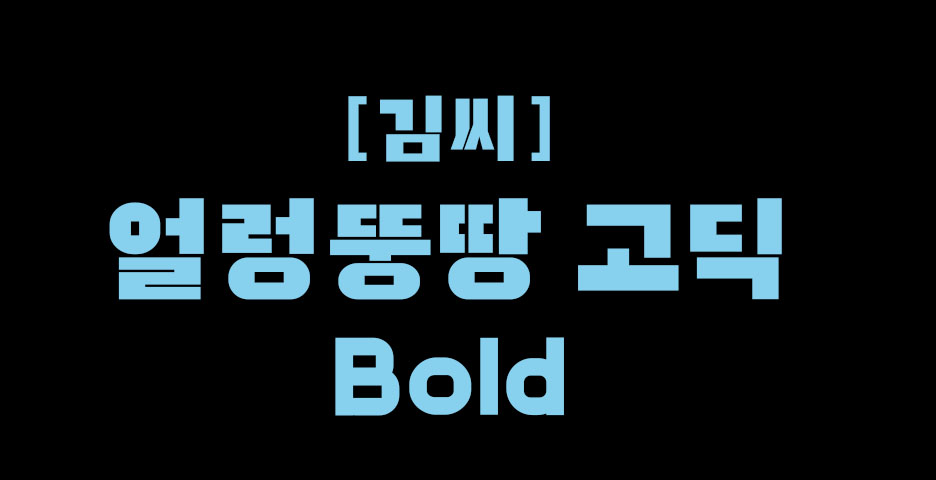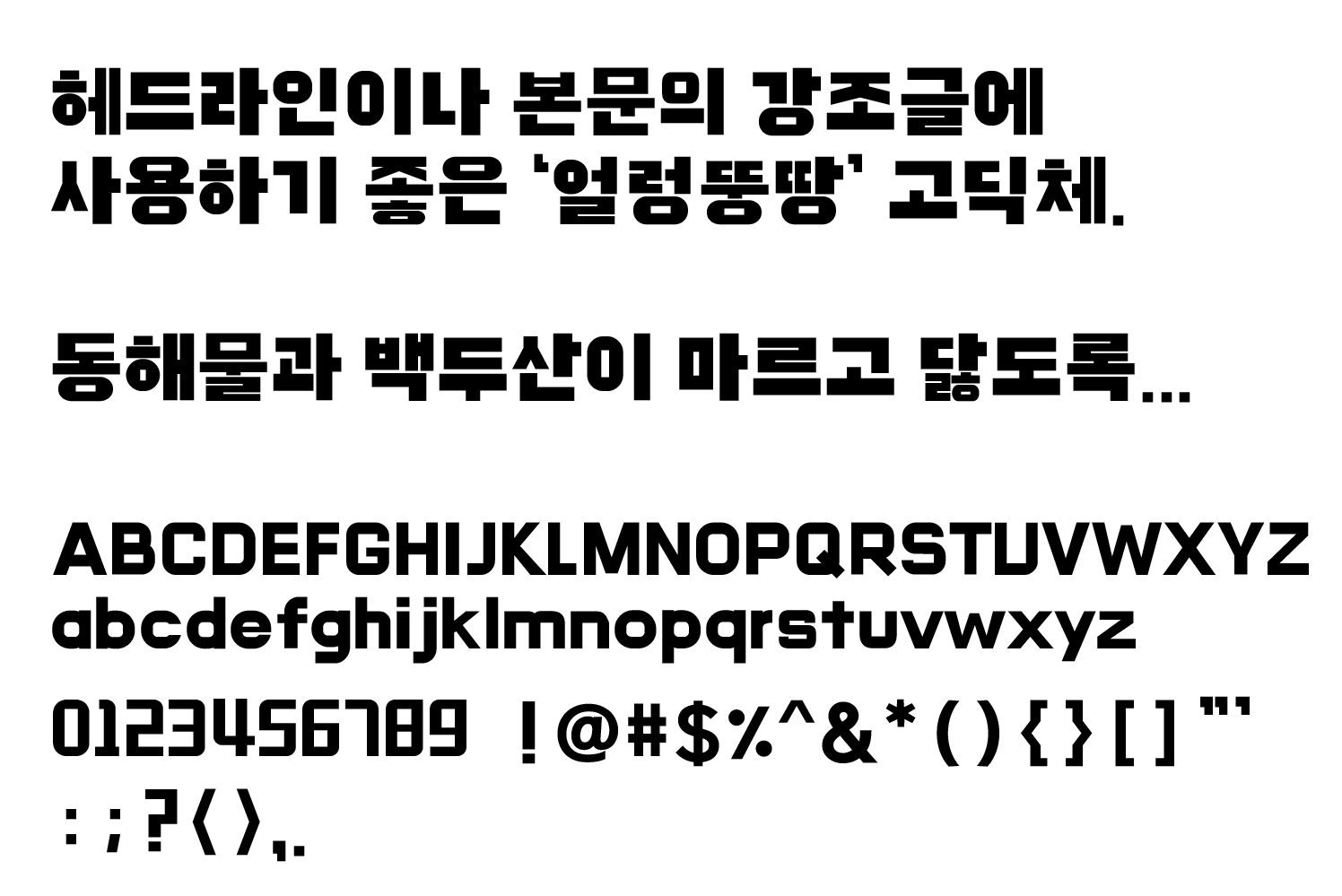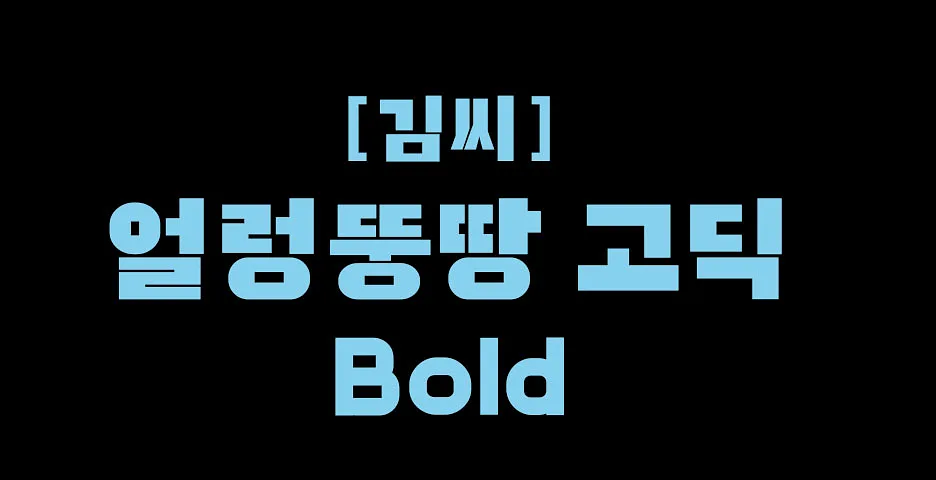
●● 폰트 특성
- 강함 / 명확함 / 신뢰감을 컨셉으로 글꼴 설계
- 전체적으로 곡선을 최소화하고 직선적인 굵은 획을 사용해서 시각적인 무게감이 느껴지도록 디자인.
- 글꼴의 장평비례가 조금 넓게 디자인되어서 문장이 답답하지 않고 리듬감 있는 블럭 형태를 형성함.
크면서도 작은 글자로 사용하기도 좋음.
●● 폰트 용도
포스터 타이틀 / 블랜드 슬로건 / 유튜브.SNS 썸네일 / 광고카피 / 이벤트 문구 등
긴 문장보다 짧고 강조되는 글에 좋음.
●● 폰트구성
1. BOLD 1종
2. 한글 11,172자
3. 영문 52자(대,소문자)
4. 숫자 10자
5.기본약물 32자
얼렁뚱땅 고딕